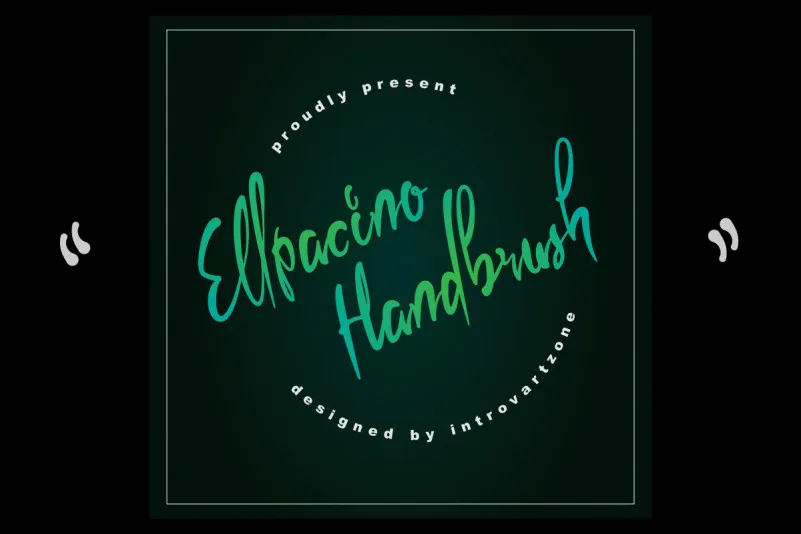
Ellpacino Handbrush Font – Fonte Grátis
Ellpacino Handbrush Font
Introduzimos a nossa nova invenção na família dos Brush Fonts: Ellpacino Handbrush Font! Esta novidade combina elegância com força, fornecendo uma tipografia script que é tanto resistente quanto versátil. Seu design inclui ligaturas perfeitas que tornam a escrita rápida e fluida. Ellpacino Handbrush foi projetada para vários usos, desde o desenho de embalagens até impressões em papel. Esta fonte também se destaca pela sua variedade de acentos, o que a torna a escolha perfeita para um amplo espectro de aplicações: desde criação de produtos impressos e cartas devidamente identificadas até design para marca. Com Ellpacino Handbrush Font, seu próximo projeto será uma arte visual incrível!